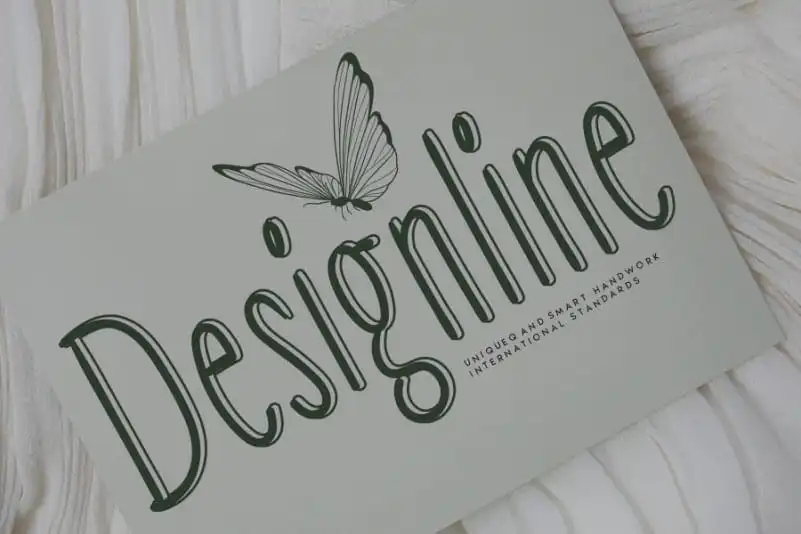
A fonte ‘Designline Display Font’ é uma criação vívida que resulta de uma harmoniosa combinação entre a caneta chifrada e a esfincio, criando um resultado incrivelmente encantador e autêntico. Suas linhas fluidas e textura única proporcionam uma aparência genuína e envolvente. Este lindo tipo de escrita manuscrita se encaixa perfeitamente em qualquer projeto DIY, oferecendo a essencial personalização necessária para transformar seus projetos em algo único e imersivo. Quebre as barreiras do design tradicional com Designline Display Font, permitindo que você crie designs autênticos e convidativos sem precisar de habilidades gráficas avançadas.